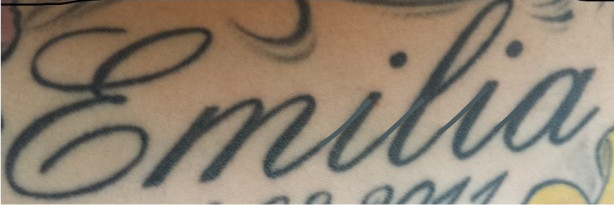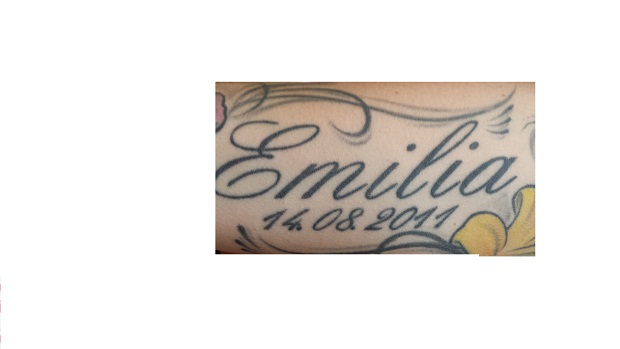
Brauche dringend Hilfe beim erkennen dieser Schrift (Emilia)
Hallo, habe mir vor mehreren Jahren den Namen meiner Tochter tätowieren lassen, nun möchte ich den Namen meines zweiten Kindes in der gleichen Schrift machen lassen, finde diese aber nicht mehr und der Tätowierer weiß es auch nicht mehr um welche Schriftart es sich hier handelt:
Also eher wie rechts als links … nur schnell hingeschubst.
Bitte sag deinem Tätowierer, er möge nicht jeden Buchstaben einzeln stechen, sondern vorher ein Wort daraus setzen.
Wollte ich auch gerade sagen. Ich finde, es wirft kein gutes Licht auf die Fähigkeiten des Tätowierers, wenn er die Buchstaben hier nicht verbindet. Man muss doch sehen, das die Schrift geradezu danach verlangt.
Ach ja, und die führende Null beim Geburtsdatum ist auch nicht gut.
Ich will ja gar nicht nur immer den Gruppenkonsens gegen den Strich bürsten, aber ich wollte gerade das genaue Gegenteil vorschlagen: Ich mein’, wo doch der Name der Tochter schon in den einzelnen Lettern steht anstatt gebunden, wäre es doch gewiss passender, auch eine führende 0 zu setzen.
Ich stimme Lars zu. Jetzt ist Konformität gefragt! Falsch weiter machen sieht besser aus als zwei unterschiedliche Versionen.
An der „0“ vor der „8“ ist nichts mehr zu ändern und ev. sieht es besser aus nun so fortzufahren. Aber bei den getrennte Buchstaben könnte der Tätowierer vielleicht noch nachbessern.